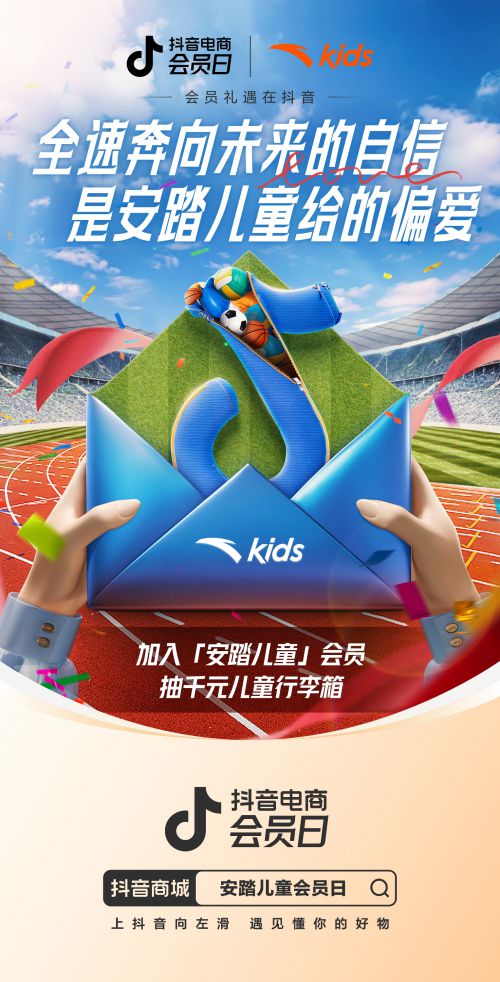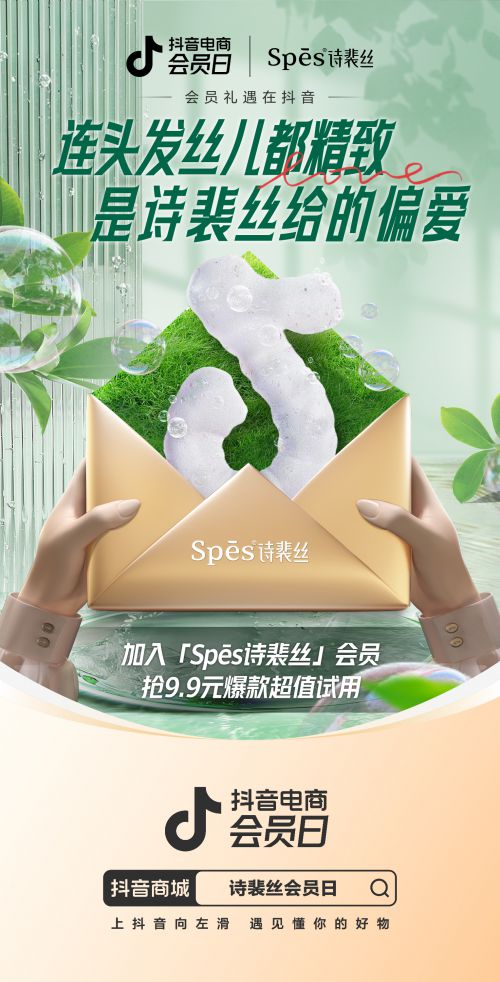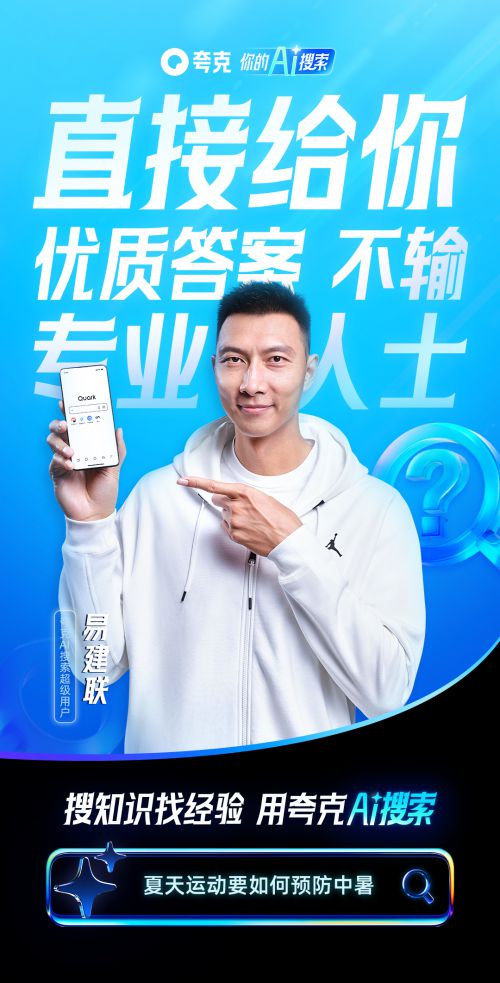
快看世界体
【快看世界体】是一款极具设计感的免费商用创意字体,支持简体中文常规字符集,适用于多元设计场景。 快看世界体采用方正字形设计,重心居中稳定,中宫宽博带来舒展的视觉体验。笔画以粗重均匀的线条为基础,方头笔型搭配利落的直角切割,部分笔画末端加入斜切处理,形成刚柔并济的独特风格。笔画间巧妙的断开设计,打破传统字体的连贯感,赋予文字现代艺术气息。 作为免费商用字体,快看世界体在保持醒目视觉张力的同时,兼具良好的阅读舒适度,适合用于广告标题、品牌LOGO、社交媒体配图等创意设计场景,助力创作者打造兼具个性与传播力的视觉作品。